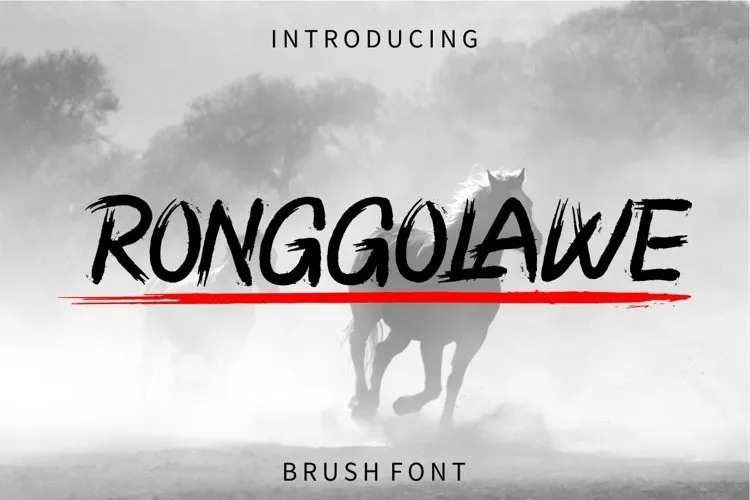
RONGGOLAWE Font – Download Grátis
A RONGGOLAWE Font é uma criação encantadora do GFR creative, desenvolvida no estilo de pintura a mão irregular. Esta fonte foi feita com um pincel digital que possui traços irregulares para produzir caracteres brutos e belos, resultando em uma tipografia impressionante e única. É perfeitamente adequada para melhorar a aparição gráfica do seu produto de forma atrativa e distintiva. Seja você um designer ou desenvolvedor gráfico, esta fonte será o complemento ideal para tornar seus projetos ainda mais memoráveis. Com uma aparência irregular e desenho robusto, ela é uma escolha perfeita para aqueles que buscam uma fonte de script com personalidade. Seja você um designer web ou gráfico, certamente vai apreciar a RONGGOLAWE Font do GFR creative.